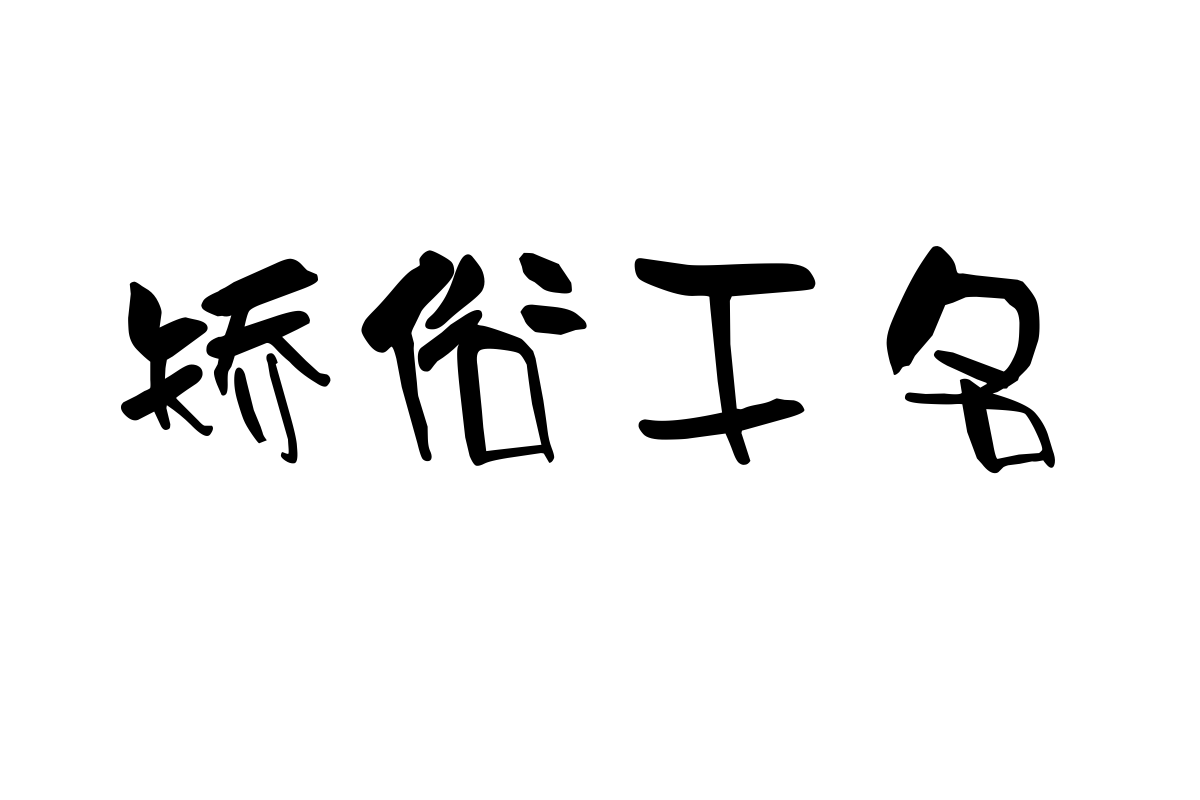
汉仪凌波体简是一种简洁的中文字体,由汉仪字库开发。它以其独特的笔画结构和优雅的字形设计,给人一种清新、自然的感觉。该字体适用于各种印刷品,如书籍、杂志、报纸、广告等,能够为视觉作品增添一份独特的美感。
汉仪凌波体简的特点如下:
1. 笔画流畅:该字体的笔画线条流畅自然,给人一种轻松愉悦的感觉。
2. 字形优美:汉仪凌波体简的字形设计独特,具有很高的辨识度和艺术价值。
3. 适用范围广:该字体适用于各种印刷品,能够满足不同场合的需求。
总之,汉仪凌波体简是一款非常实用的中文字体,适合用于需要展现优雅、清新风格的设计作品。